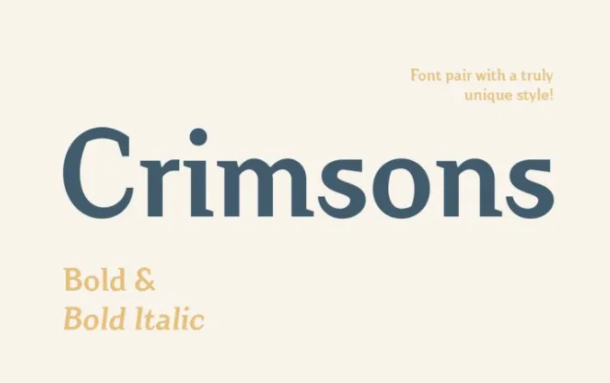
Fontbundles Crimsons Font (2021)
Встречайте уникальный шрифт Crimsons Bold и его наклонную версию Crimsons Bold Italic.
Иногда нам нужно всего несколько граней, чтобы воплотить в жизнь наши творческие идеи. Для этой цели мы разделили некоторые из наших популярных семейств шрифтов на вполне достаточные пары.
Crimsons - уникальный и очень необычный шрифт, он сочетает в себе современный гротеск, средневековые мотивы и пропорции засечек. Эти шрифты станут полезной частью дизайнерской коллекции. Crimsons идеально подходит для коротких и эмоциональных надписей. Заголовки, имена, логотипы - это его стихия.